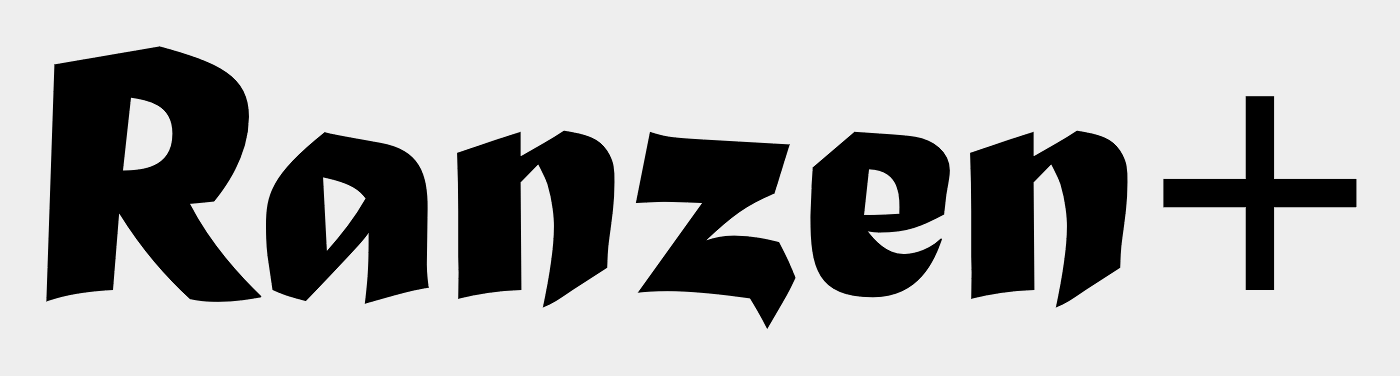
Kennt jemand diese gebrochene Schrift?
kann mir jemand sagen, wie diese Schrift heisst? Sie müsste entweder aus den Anfängen des Computerzeitalter stammen (vielleicht auf Windows erstellt?) oder evtl. Handgeschrieben sein. Ich habe euch das Beispiel in den Anhang gelegt. Leider habe ich nicht mehr als diese paar Buchstaben. Mein Kunde möchte diesen Schriftzug beibehalten und ich kann nichts im Netz dazu finden.
mir sieht das sehr nach einer frühen coreldraw-schrift aus.
Zumindest die Gemeinen sind Matura: